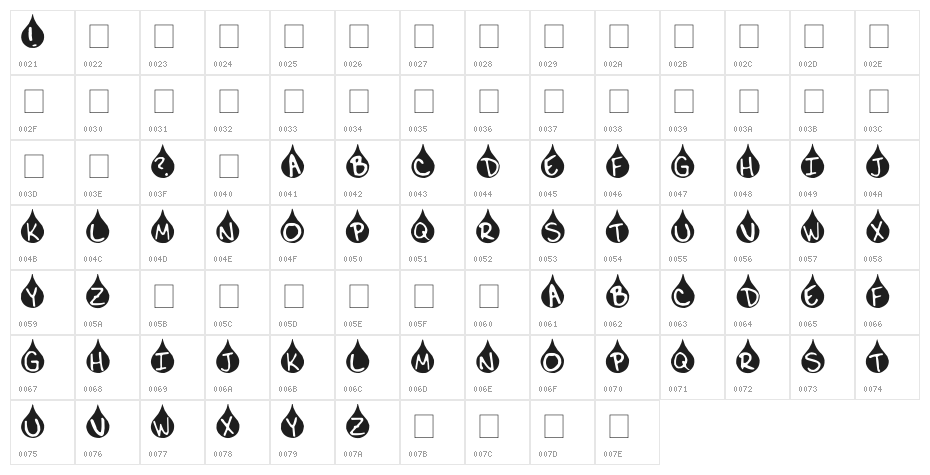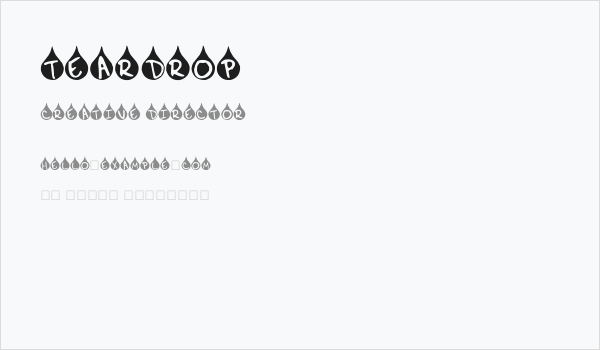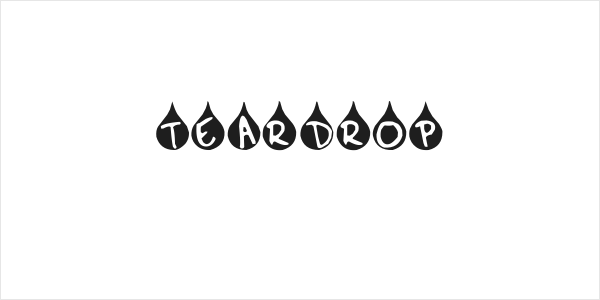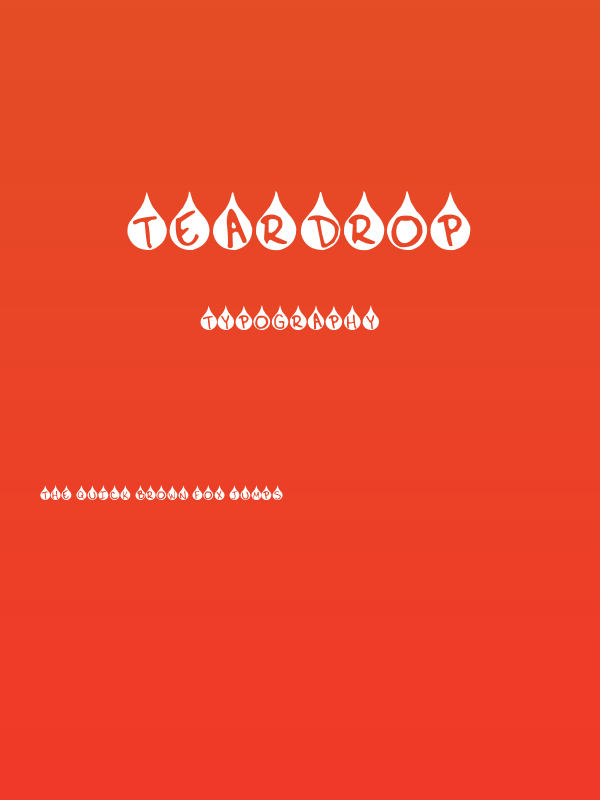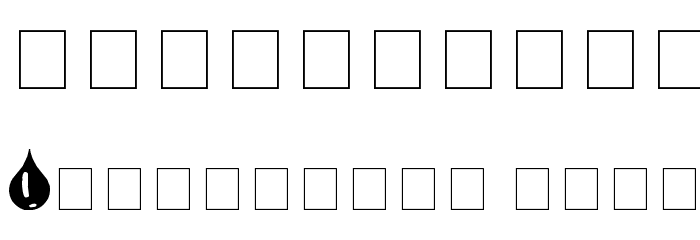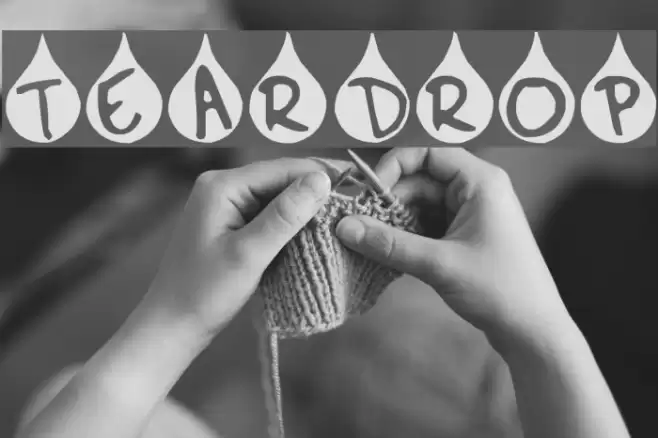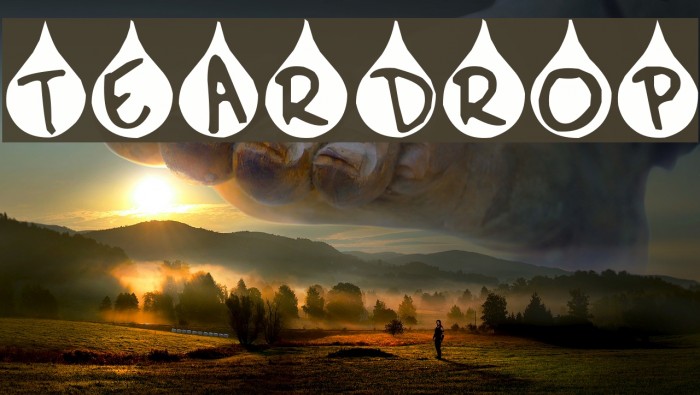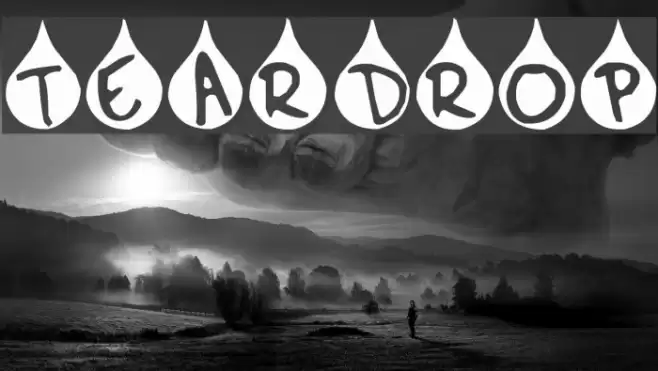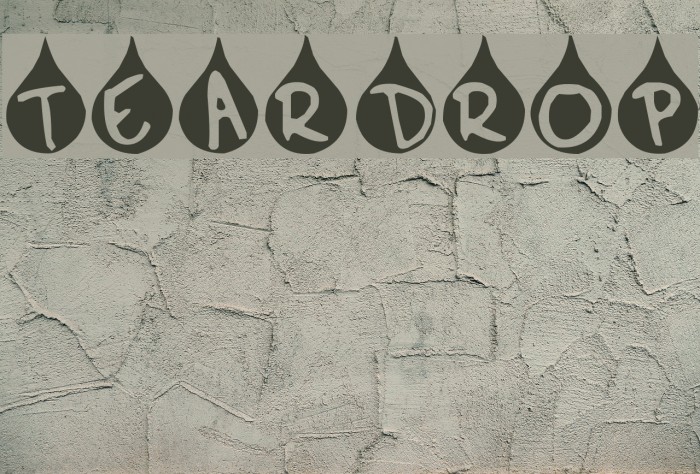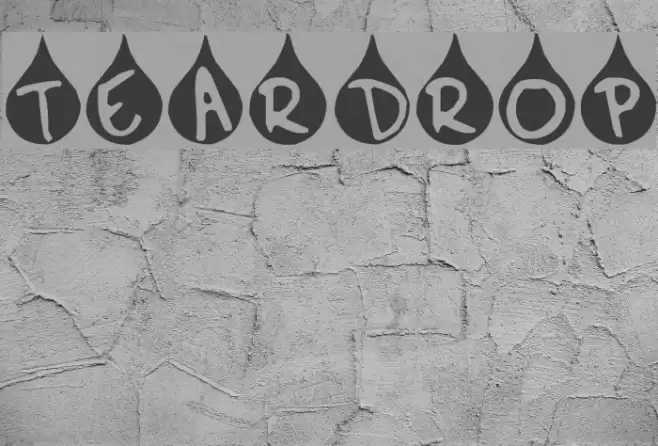
Teardrop Font
| Gesamtstil | Whimsical, Decorative |
| Vorgeschlagene Projekte | Ideal for children's books, playful branding, artistic posters, and creative invitations. |